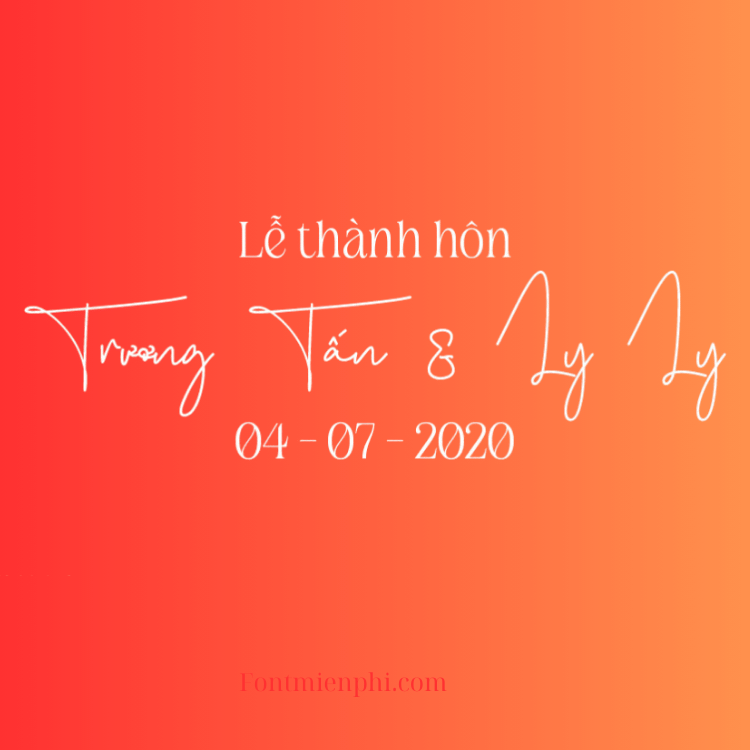
Font Việt hóa Fashion Signature VIP
Giới thiệu về Font Việt hóa Fashion Signature VIP
Trong thế giới đồ họa hiện đại, việc lựa chọn một Font Miễn Phí chất lượng luôn là ưu tiên hàng đầu của các nhà thiết kế. Đặc biệt, bộ Font Việt hóa Fashion Signature VIP nổi lên như một biểu tượng của sự sang trọng và tinh tế. Đây là phông chữ dạng chữ ký tay với những đường nét uyển chuyển, thanh thoát, cực kỳ phù hợp cho các dự án liên quan đến làm đẹp, thời trang cao cấp hoặc thương hiệu cá nhân. Việc sở hữu bộ font này giúp bản thiết kế của bạn trở nên chuyên nghiệp và có hồn hơn bao giờ hết.
Đặc điểm nổi bật của phông chữ
Điểm làm nên sự khác biệt của Font Việt hóa Fashion Signature VIP chính là sự kết hợp hoàn mỹ giữa nét vẽ tay tự nhiên và cấu trúc ký tự hiện đại. Các ký tự được tinh chỉnh tỉ mỉ, hỗ trợ đầy đủ dấu tiếng Việt giúp người dùng không gặp lỗi khi gõ văn bản. Với độ tương phản nhẹ nhàng, phông chữ này mang lại cảm giác phóng khoáng nhưng vẫn giữ được sự chỉn chu cần thiết cho các ấn phẩm in ấn hoặc banner quảng cáo kỹ thuật số.
Ứng dụng thực tế của Font Việt hóa Fashion Signature VIP
Bộ font này cực kỳ đa năng trong nhiều lĩnh vực khác nhau. Bạn có thể sử dụng nó để tạo ra những mẫu logo chữ ký độc bản, làm tiêu đề cho bìa tạp chí thời trang hoặc trang trí thiệp mời sự kiện. Ngoài ra, các bạn học sinh và sinh viên cũng có thể dùng phông chữ này để làm nổi bật tiêu đề bài thuyết trình, giúp nội dung trở nên thu hút và nghệ thuật hơn.